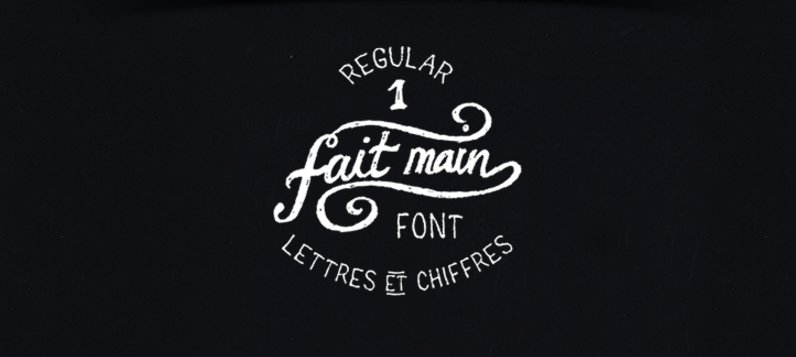
Fait Main Font – Download Grátis
A Fait Main Font é uma escolha perfeita para quem busca uma fonte escrita a mão que se adapta a diversos estilos sem comprometer a qualidade e elegância, especialmente na área de roupas e produtos personalizados como adesivos ou etiquetas. Esta fonte foi criada por Ju Dzign e incorpora um estilo único e atraente. Ela é perfeitamente adaptável para diferentes usos, desde materiais em formato de selo até tags de rótulos. Para explorar mais recursos do designer Hamilton, visite http://www.judzign.com.